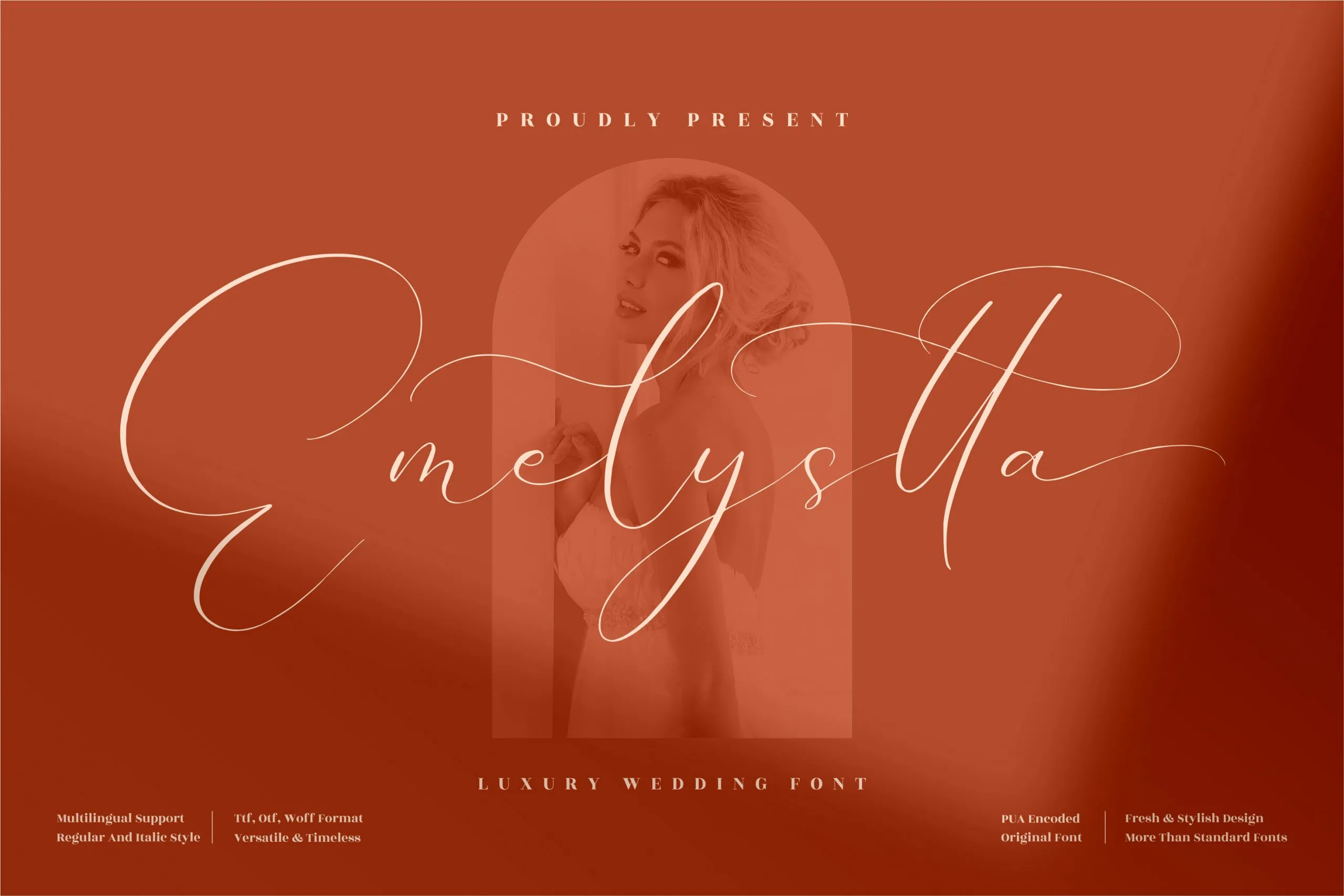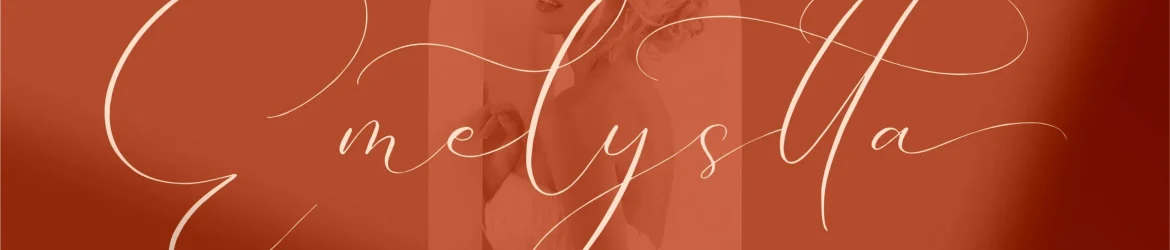
A Emelystta Font é uma elegante tipografia script que se destaca por sua riqueza de detalhes e sensibilidade. Desenvolvida pelo estúdio Perspectype, ela traz um toque romântico do mundo da caligrafia que enriquece qualquer projeto. Esta fonte perfeita para aplicações como logotipos, projetos de marca, designs de móveis de casa, embalagens de produtos, tigelas e xícaras, frases, cartazes, bolsas de shopping, camisetas, capas de livro, cartões de nome, convites, cartões de agradecimento, etiquetas, fotografia e até mesmo embaixadores de eventos especiais. A Emelystta é uma escolha perfeita para aqueles que buscam um toque delicado no design de qualquer projeto visual.